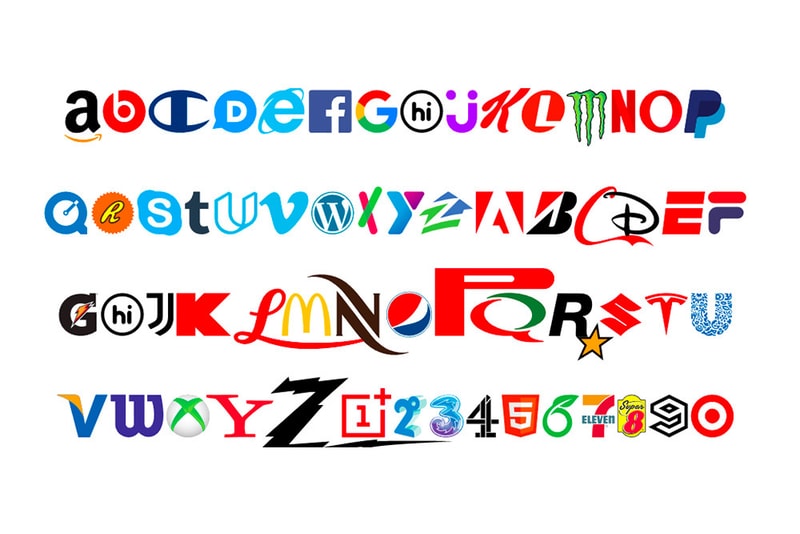
Hello Velocity 整合新字体致敬现今消费主义
用上都是各位应该不陌生的公司徽标。
不知道各位日常消费时,会留意到品牌标记,毕竟每个品牌标记的设计都各花心思,充满意义。而最近一间数码工作室 Hello Velocity 便整合出一套 Typeface 新字体「Brand New Roman」,以对围绕我们的消费主义作出明确的陈述致敬。整套字体 Hello Velocity 希望带来发人深思的互联网体验,当中包括 76 个英文及数字,熟悉的商标亦包括 Amazon,McDonalds,Facebook,Tesla,Disney 等,都是各大家生活息息相关。而 Hello Velocity 亦特别制作出 Chrome 及 Firefox 网页插件,让大家网页换成这互动广告牌,大家也可以点击 Hello Velocity 网站去使用 Brand New Roman 字体。